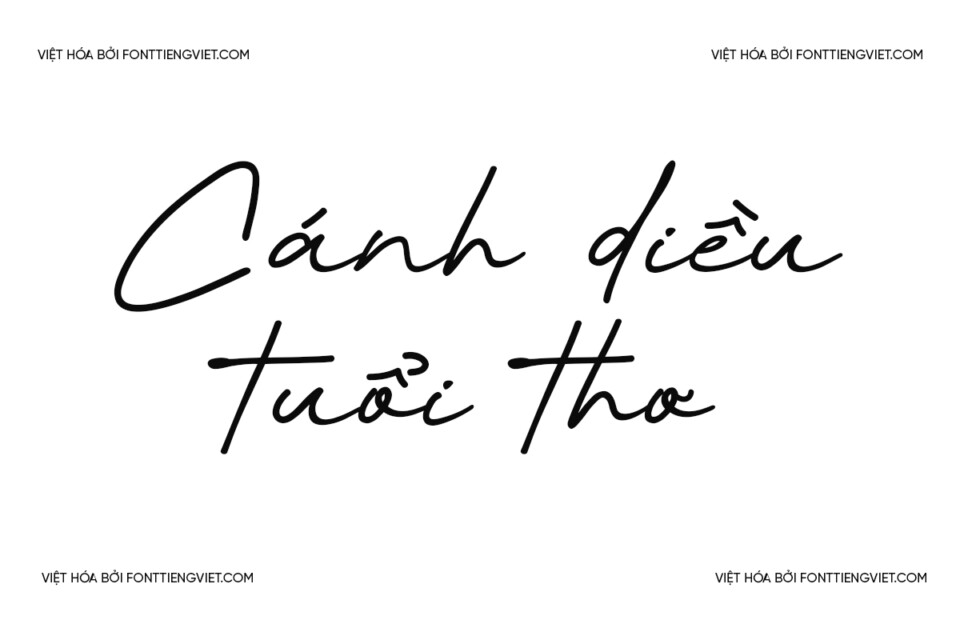
Phông chữ đóng vai trò thiết yếu trong việc truyền tải thông điệp, đặc biệt là trong môi trường học đường và các dự án thiết kế sáng tạo. Một Font Chữ đẹp, dễ đọc và truyền cảm hứng có thể nâng cao đáng kể chất lượng bài thuyết trình, báo cáo hay các ấn phẩm giáo dục. Hôm nay, chúng ta sẽ cùng đi sâu vào tìm hiểu về “Font Việt hóa 1FTV VIP High Empathy” – một lựa chọn hoàn hảo mang đến sự kết hợp tinh tế giữa tính thẩm mỹ, khả năng dễ đọc và yếu tố cảm xúc sâu sắc. Phông chữ này không chỉ đơn thuần là một công cụ hiển thị văn bản mà còn là một phương tiện mạnh mẽ để tạo ra sự kết nối, đặc biệt hữu ích cho học sinh, sinh viên và những ai đang chuẩn bị cho các kỳ thi tốt nghiệp quan trọng, nơi sự rõ ràng và ấn tượng là chìa khóa thành công.
Font Việt hóa 1FTV VIP High Empathy: Sự Lựa Chọn Hoàn Hảo Cho Mọi Dự Án
“Font Việt hóa 1FTV VIP High Empathy” là một thành tựu đáng chú ý trong lĩnh vực thiết kế phông chữ, đặc biệt là với phiên bản Việt hóa hoàn chỉnh. Nó được thiết kế với triết lý đặt cảm xúc và trải nghiệm người dùng lên hàng đầu. Điều này không chỉ thể hiện qua từng nét chữ mượt mà, cân đối mà còn ở khả năng khơi gợi sự đồng cảm và kết nối với người đọc. Đối với giáo dục, việc sử dụng một phông chữ như thế này có thể giúp làm giảm căng thẳng thị giác, khuyến khích sự tập trung và tạo ra một môi trường học tập trực quan thân thiện hơn. Sự kết hợp giữa tính chuyên nghiệp và yếu tố nhân văn giúp phông chữ này trở thành công cụ đắc lực cho mọi người, từ giáo viên, học sinh phổ thông cho đến sinh viên đại học.
Đặc Điểm Nổi Bật Của Font Việt hóa 1FTV VIP High Empathy
Một trong những đặc điểm nổi bật nhất của “Font Việt hóa 1FTV VIP High Empathy” chính là khả năng truyền tải cảm xúc một cách tinh tế. Các nhà thiết kế đã chú trọng đến từng chi tiết nhỏ, từ độ cong của nét chữ, khoảng cách giữa các ký tự cho đến cách thức chúng tương tác với nhau để tạo ra một tổng thể hài hòa và dễ chịu. Sự “High Empathy” trong tên gọi không phải là ngẫu nhiên; nó phản ánh mục tiêu của font chữ là tạo ra một cầu nối cảm xúc giữa nội dung và người đọc. Đặc biệt, phiên bản Việt hóa đã được tối ưu hóa cẩn thận để đảm bảo tất cả các dấu tiếng Việt đều hiển thị đẹp mắt, rõ ràng và không gây khó chịu, điều mà nhiều phông chữ khác thường gặp phải. Điều này làm cho nó trở thành một công cụ không thể thiếu cho các tài liệu học tập, sách giáo khoa, bài giảng và các dự án thiết kế mang đậm bản sắc Việt.
Tầm Quan Trọng Của Font Chữ Có Cảm Xúc Trong Giáo Dục
Trong bối cảnh giáo dục hiện đại, việc thu hút sự chú ý và duy trì hứng thú của học sinh là vô cùng quan trọng. Một phông chữ có khả năng gợi cảm xúc như “Font Việt hóa 1FTV VIP High Empathy” có thể đóng góp tích cực vào mục tiêu này. Nó giúp làm cho các tài liệu học tập trở nên sinh động và ít khô khan hơn, từ đó khuyến khích học sinh, sinh viên tương tác nhiều hơn với nội dung. Phông chữ này cũng đặc biệt phù hợp cho việc thiết kế các poster, infographic hoặc các tài liệu truyền thông nội bộ trường học, nơi cần sự thân thiện, gần gũi nhưng vẫn đảm bảo tính chuyên nghiệp. Khả năng dễ đọc cao của nó cũng là một lợi thế lớn, đặc biệt đối với học sinh trung học phổ thông đang phải tiếp nhận lượng kiến thức lớn, giúp các em tập trung vào nội dung thay vì phải vật lộn với việc giải mã ký tự.
Ứng Dụng Của Font Việt hóa 1FTV VIP High Empathy Trong Học Đường và Thiết Kế
Phạm vi ứng dụng của “Font Việt hóa 1FTV VIP High Empathy” trong môi trường học đường và các lĩnh vực sáng tạo là vô cùng rộng lớn. Từ việc tạo ra các bài thuyết trình ấn tượng, báo cáo khoa học dễ hiểu cho đến thiết kế các ấn phẩm quảng bá sự kiện trường học, phông chữ này đều mang lại giá trị vượt trội. Nó giúp các dự án cá nhân của học sinh trở nên chuyên nghiệp hơn, đồng thời hỗ trợ các giáo viên trong việc tạo ra tài liệu giảng dạy hấp dẫn và hiệu quả. Khả năng tùy biến cao của phông chữ cũng cho phép người dùng linh hoạt điều chỉnh để phù hợp với nhiều phong cách và mục đích khác nhau, từ những dự án đòi hỏi sự nghiêm túc cho đến những ý tưởng cần sự sáng tạo và bay bổng.
Nâng Cao Trải Nghiệm Học Tập Cho Học Sinh và Sinh Viên
Đối với học sinh, sinh viên, việc trình bày rõ ràng và hấp dẫn là chìa khóa để đạt điểm cao trong các bài tập, dự án. “Font Việt hóa 1FTV VIP High Empathy” cung cấp một giải pháp hoàn hảo để làm cho các bài viết, bài thuyết trình trở nên nổi bật hơn. Tính dễ đọc và vẻ ngoài thân thiện của phông chữ giúp giảm bớt gánh nặng thị giác, cho phép người đọc dễ dàng tiếp thu thông tin. Điều này đặc biệt quan trọng đối với các bài luận dài, báo cáo nghiên cứu hoặc tài liệu học tập tự biên soạn. Việc sử dụng phông chữ này còn thể hiện sự chuyên nghiệp và chỉn chu của người thực hiện, giúp tạo ấn tượng tốt với giáo viên và bạn bè. Nó thực sự là một trợ thủ đắc lực trong hành trình chinh phục tri thức.
Tạo Ấn Tượng Mạnh Mẽ Trong Các Bài Thi Tốt Nghiệp và Dự Án
Các kỳ thi tốt nghiệp và dự án cuối cấp thường đòi hỏi sự đầu tư lớn về cả nội dung và hình thức. Một bài luận hay báo cáo được trình bày bằng “Font Việt hóa 1FTV VIP High Empathy” sẽ ngay lập tức tạo được sự khác biệt. Phông chữ này không chỉ đảm bảo tính rõ ràng, dễ đọc – yếu tố cực kỳ quan trọng khi giám khảo phải chấm rất nhiều bài – mà còn toát lên vẻ tinh tế, chuyên nghiệp và có chiều sâu. Đối với học sinh trung học phổ thông, việc sử dụng một phông chữ chất lượng có thể giúp bài làm của các em trở nên nổi bật giữa hàng trăm bài khác, thể hiện sự nghiêm túc và tôn trọng đối với bài thi. Điều này góp phần không nhỏ vào việc tạo ra một ấn tượng tích cực ban đầu, có thể ảnh hưởng đến cách đánh giá tổng thể của giám khảo.
Vai Trò Trong Thiết Kế Đồ Họa Và Thương Hiệu Cá Nhân
Ngoài các ứng dụng học thuật, “Font Việt hóa 1FTV VIP High Empathy” cũng là một tài sản quý giá cho các nhà thiết kế đồ họa và những người muốn xây dựng thương hiệu cá nhân. Với vẻ đẹp hiện đại nhưng vẫn mang đậm dấu ấn cảm xúc, phông chữ này phù hợp để thiết kế logo, banner, thiệp mời, hồ sơ cá nhân hoặc các ấn phẩm truyền thông khác. Nó giúp tạo ra một phong cách riêng biệt, dễ nhận diện và có khả năng kết nối mạnh mẽ với khán giả. Tính Việt hóa hoàn chỉnh cũng mở ra nhiều cơ hội cho các dự án thiết kế hướng đến thị trường Việt Nam, đảm bảo thông điệp được truyền tải một cách tự nhiên và hiệu quả nhất, không bị lỗi font hay mất dấu như nhiều phông chữ nước ngoài khác.
Tổng kết lại, “Font Việt hóa 1FTV VIP High Empathy” không chỉ là một phông chữ Việt hóa thông thường mà còn là một công cụ mạnh mẽ giúp bạn truyền tải thông điệp một cách hiệu quả và đầy cảm xúc. Từ việc nâng cao chất lượng học tập cho học sinh, sinh viên, đến việc tạo ra sự khác biệt trong các bài thuyết trình hay dự án cá nhân, phông chữ này đều chứng minh được giá trị vượt trội của mình. Với những đặc tính ưu việt về tính nhân văn, khả năng dễ đọc và sự tinh tế trong thiết kế, “Font Việt hóa 1FTV VIP High Empathy” chắc chắn sẽ là một tài sản quý giá cho bất kỳ ai muốn tạo ra nội dung ấn tượng và giàu ý nghĩa. Hãy trải nghiệm sức mạnh của Font Chữ này để biến ý tưởng của bạn thành hiện thực một cách chuyên nghiệp và đầy cuốn hút.